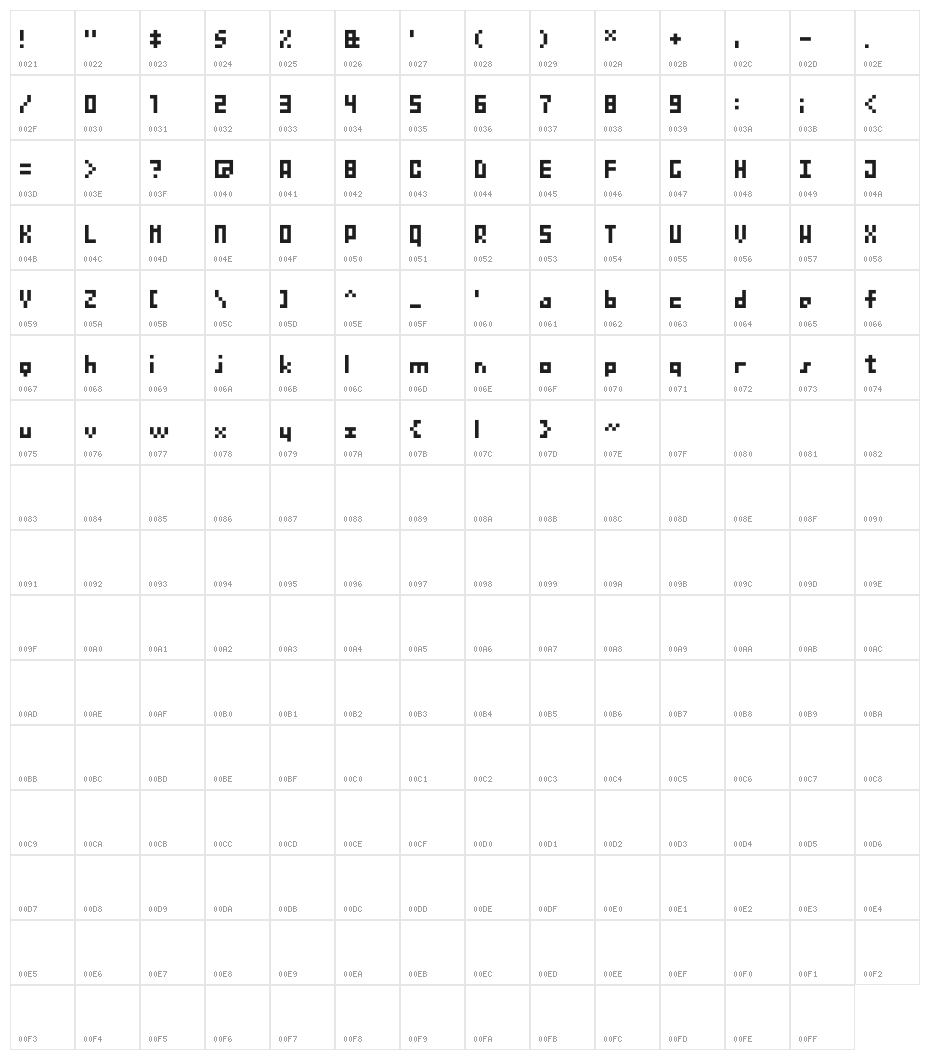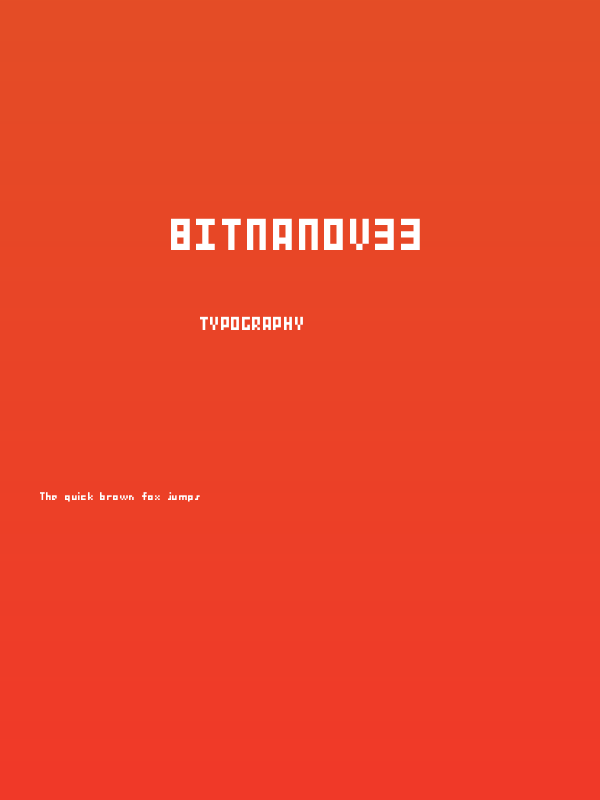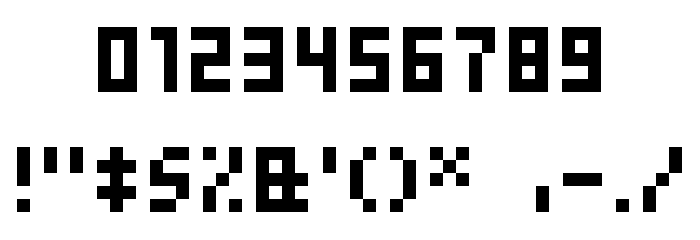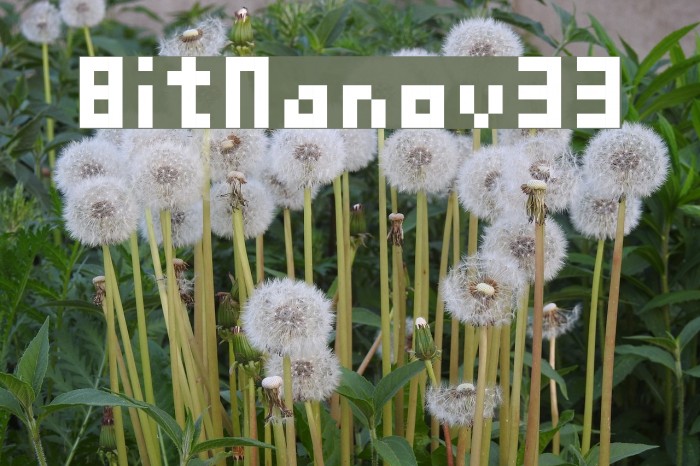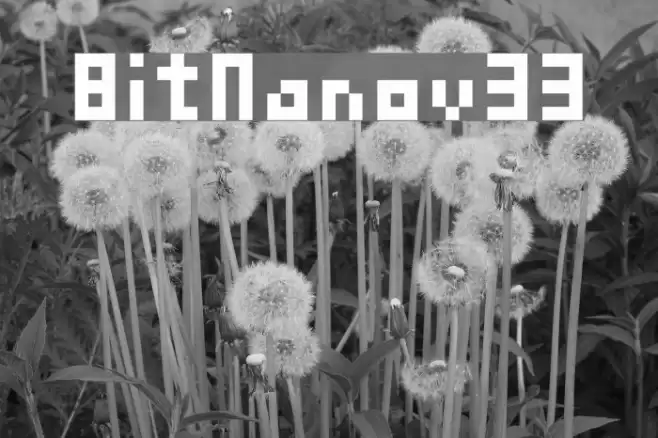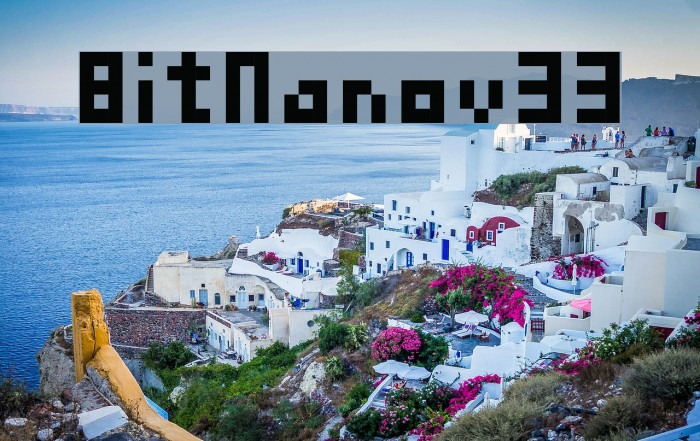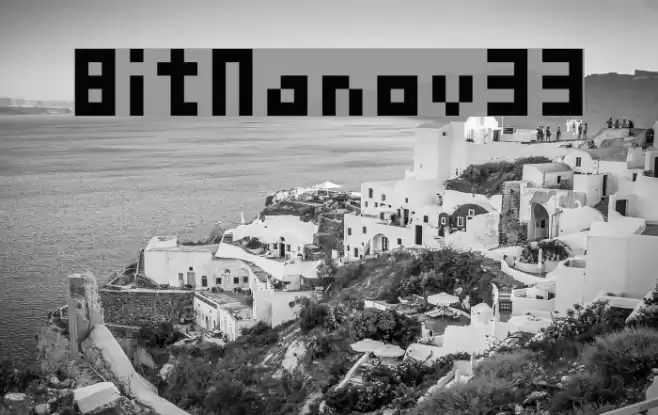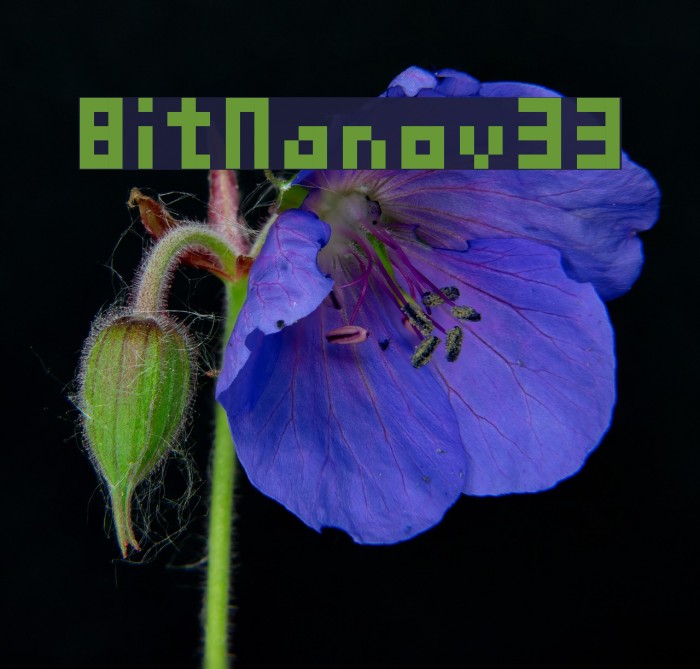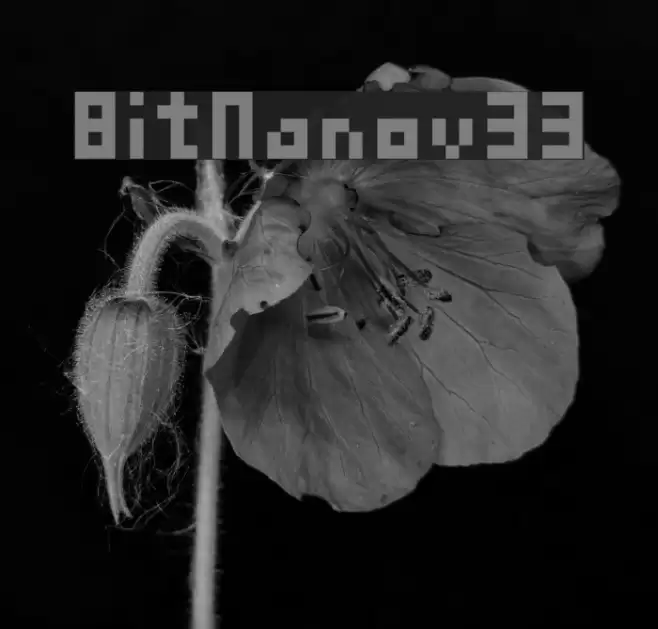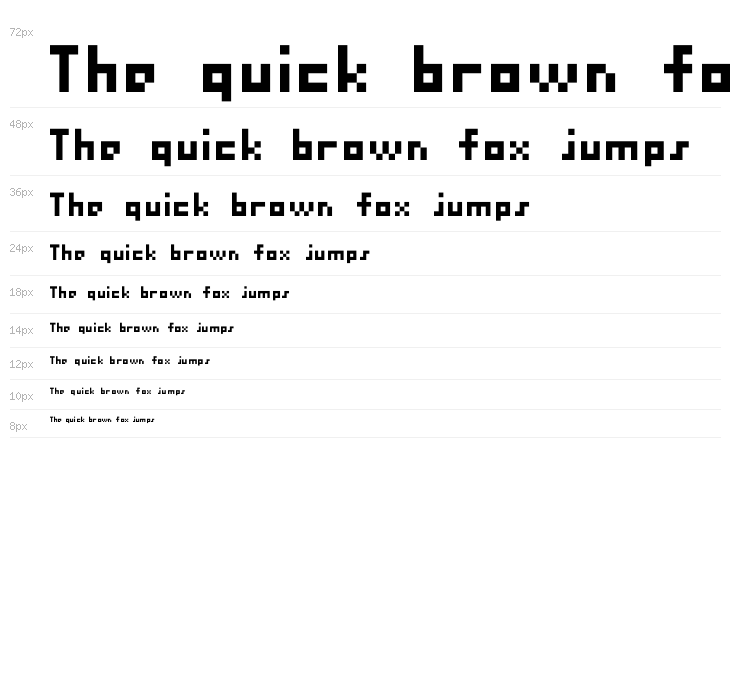
BitNanov33 Font
✎ Pixel
| Kategorien | Pixel |
| Gesamtstil | Retro, Digital |
| Anwendungsfall | Headlines, Logos, Digital Art |
| Vorgeschlagene Projekte | Ideal for video game design, digital art projects, retro-themed posters, and any creative work that seeks to evoke a sense of nostalgia for early digital technology. |